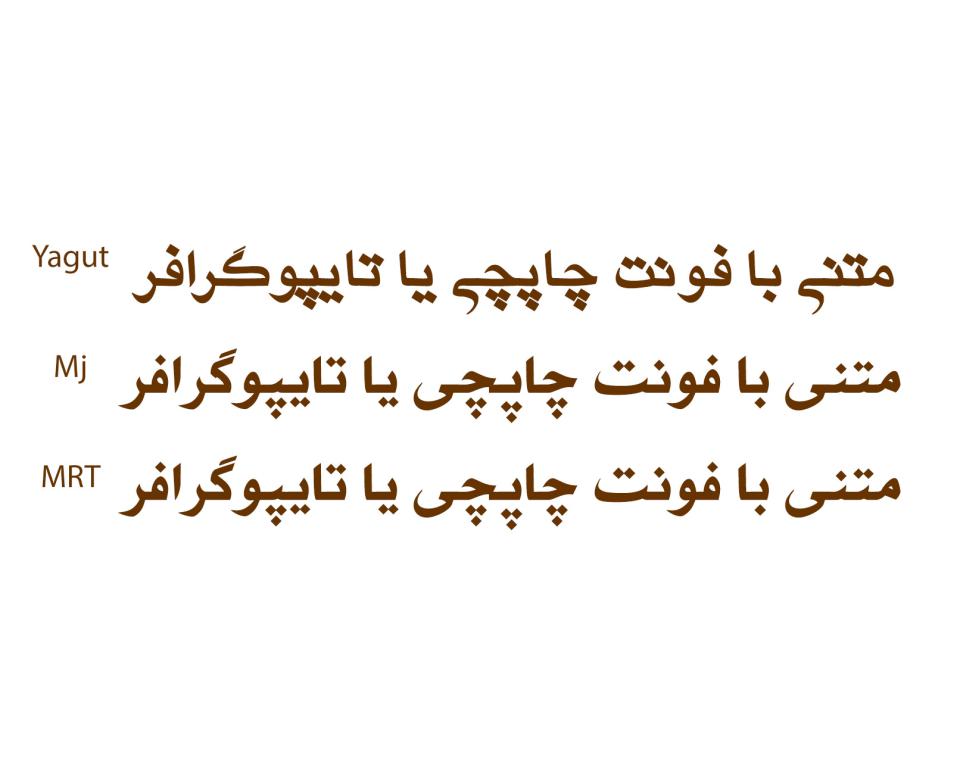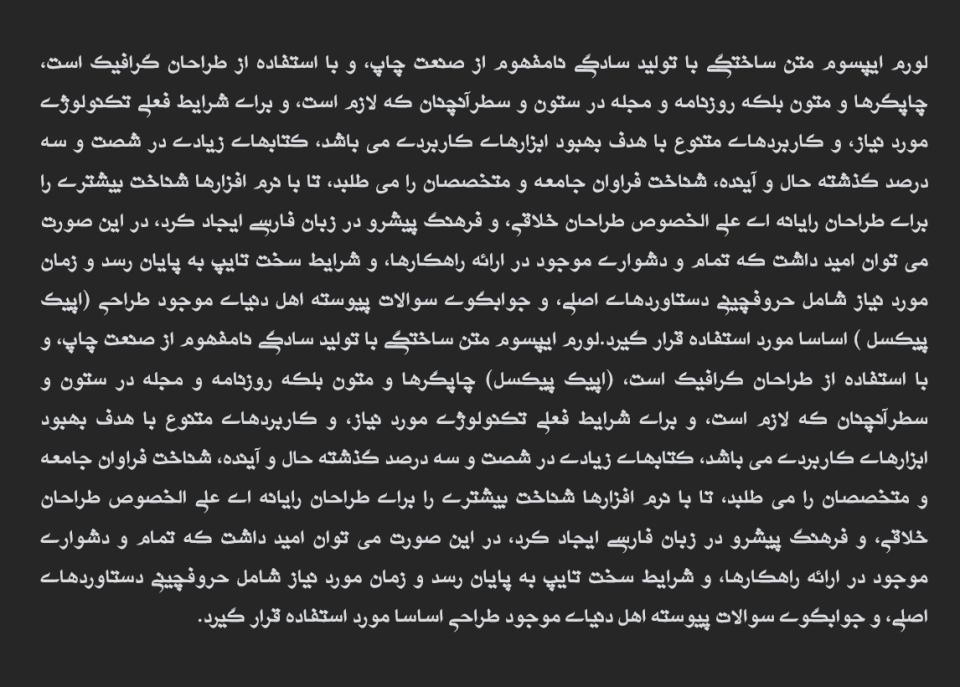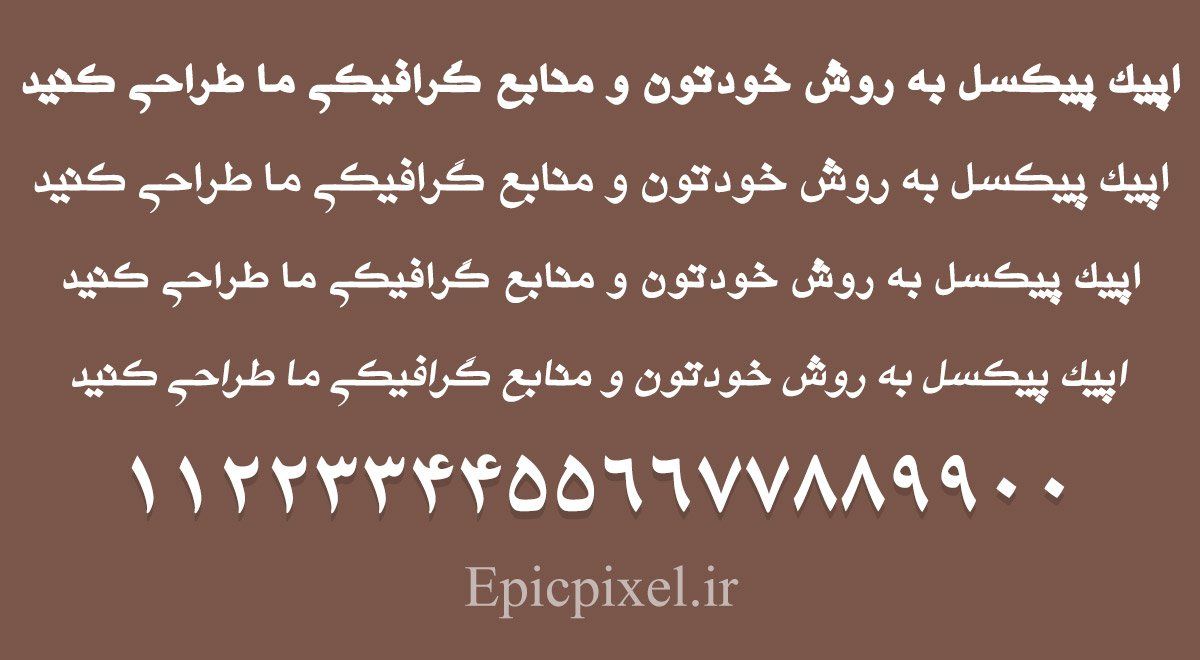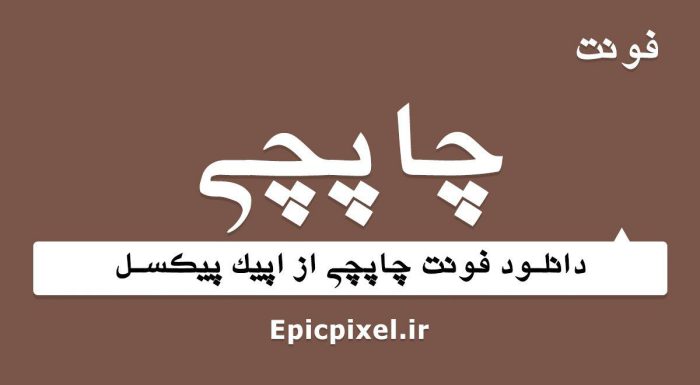
13 فونت چاپچی فارسی Typographer
فونت چاپچی، که با نام فونت تایپوگرافر هم شناخته می شود، یک انتخاب جذاب برای کسانی است که به دنبال ترکیبی از سنت و مدرنیته در نوشته های خود هستند. این فونت، با لبه های نوک تیز حروف، حس و حالی نوستالژیک را زنده می کند و در عین حال، ساختاری مدرن و خوانا دارد. این ویژگی باعث می شود که هم در طراحی های چاپی و هم در محیط های دیجیتال، به خوبی بدرخشد.
یکی از ویژگی های برجسته فونت چاپچی، تنوع وزن های آن است. از وزن های سنگین (Heavy) برای عناوین قدرتمند گرفته تا وزن های معمولی (Normal) و کتابی (Book) برای متن های طولانی تر، این فونت انعطاف پذیری بالایی را ارائه می دهد. این تنوع به طراحان اجازه می دهد تا با استفاده از وزن های مختلف، سلسله مراتب بصری جذابی را در طرح های خود ایجاد کنند.
جالب است بدانید این فونت یک وزن خاص به نام یاقوت (Yagut) هم دارد. این وزن، رویکردی مدرن به تایپوگرافی ارائه می دهد. پیچش های ظریف در انتهای حروف و نقاط لوزی شکل، به نوشته ها جلوه ای خاص و متفاوت می بخشد. این ویژگی، به ویژه برای طراحی لوگو، پوستر و سایر مواردی که نیاز به ظاهری منحصربه فرد دارند، بسیار مناسب است.
فونت چاپچی، با وجود شباهت هایی که به فونت های رایج مانند آریال و تایمز نیو رومن دارد، تفاوت های چشمگیری نیز دارد. طراحی خاص این فونت، آن را از سایر فونت ها متمایز می کند و به نوشته ها شخصیتی ویژه می بخشد. این فونت به صورت رایگان در دسترس است و می تواند گزینه ای ایده آل برای طراحانی باشد که به دنبال فونتی باکیفیت و در عین حال رایگان هستند. اگر به دنبال فونتی هستید که هم حس نوستالژیک داشته باشد و هم مدرن به نظر برسد، فونت چاپچی (تایپوگرافر) انتخابی عالی است.